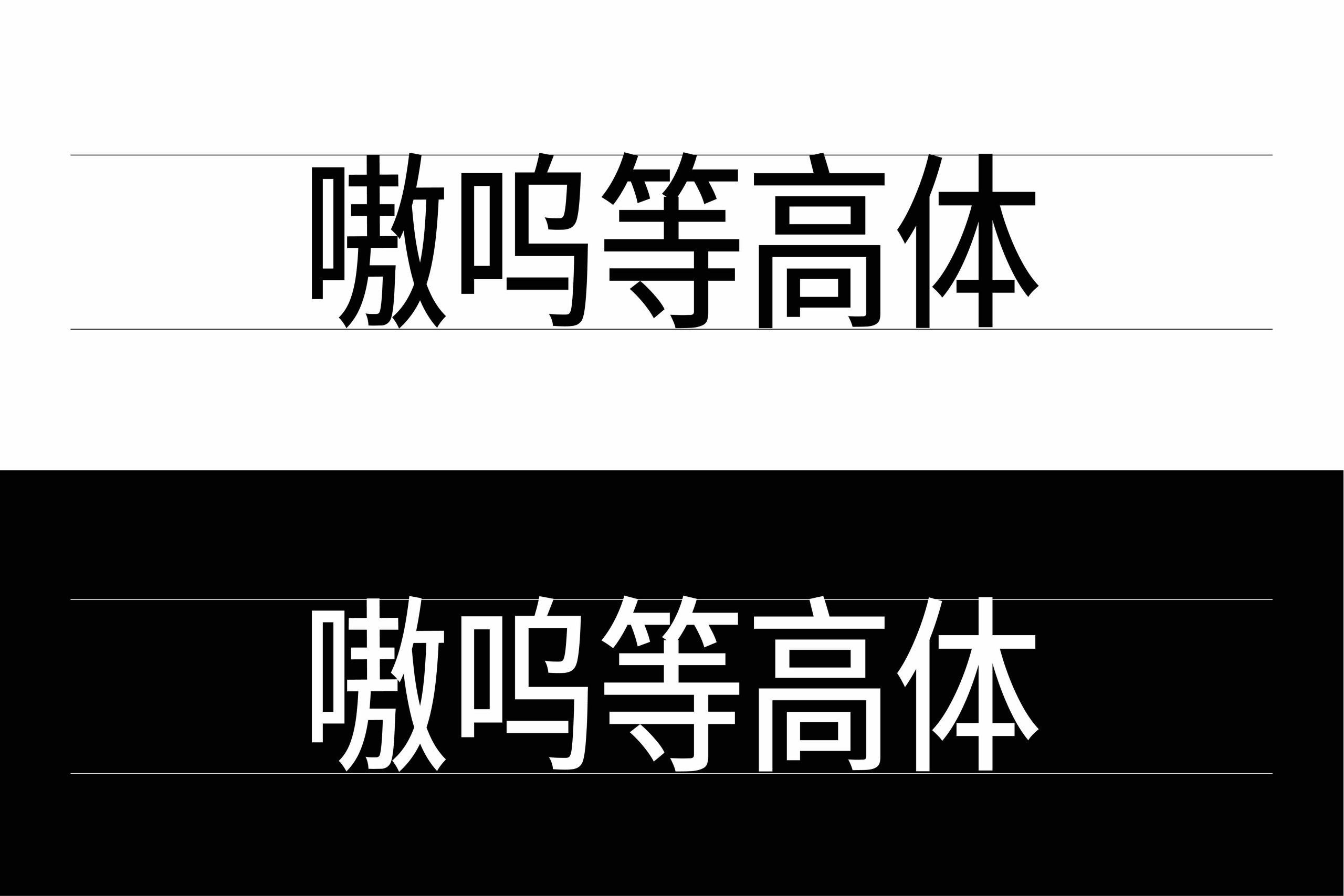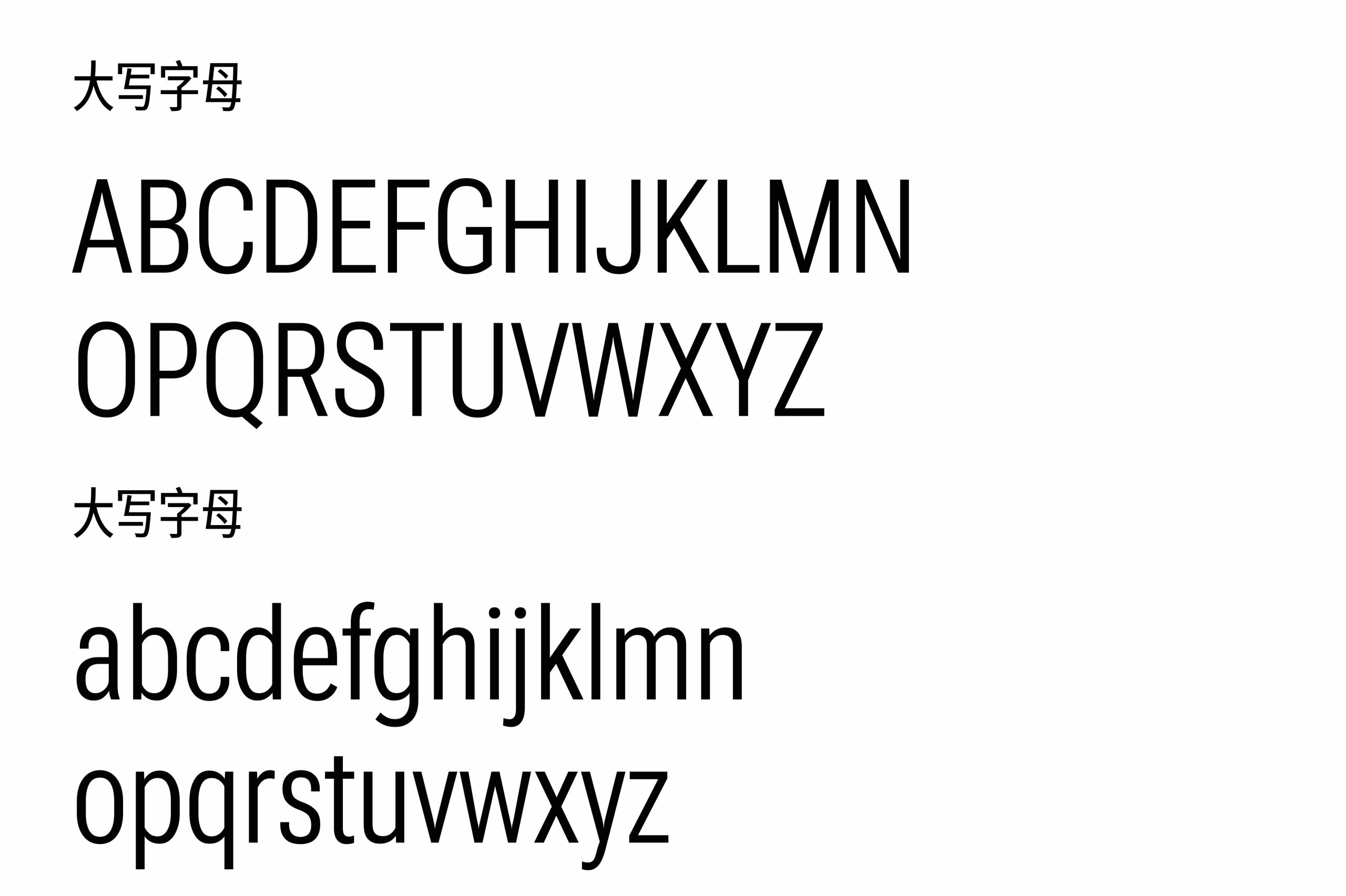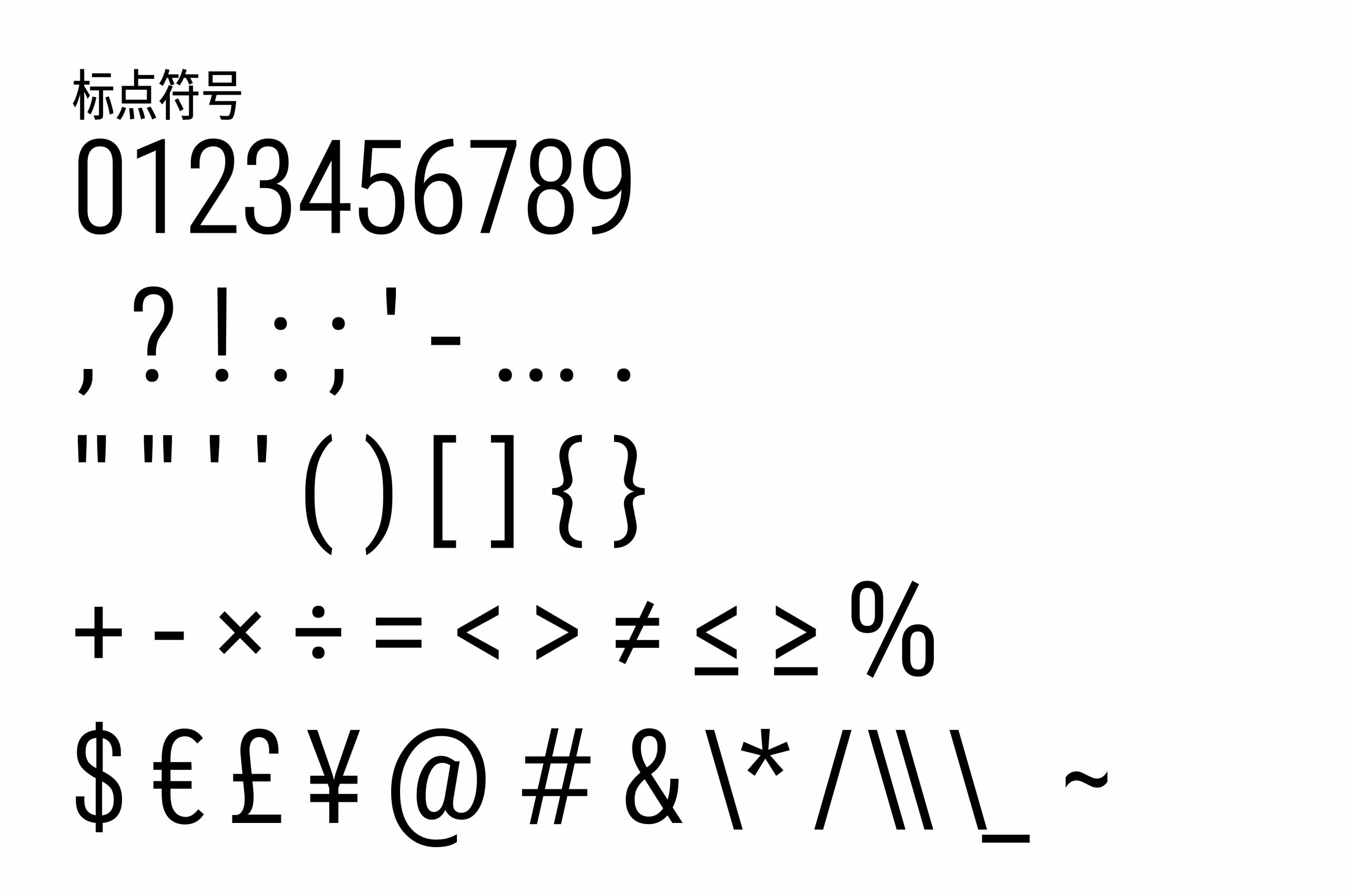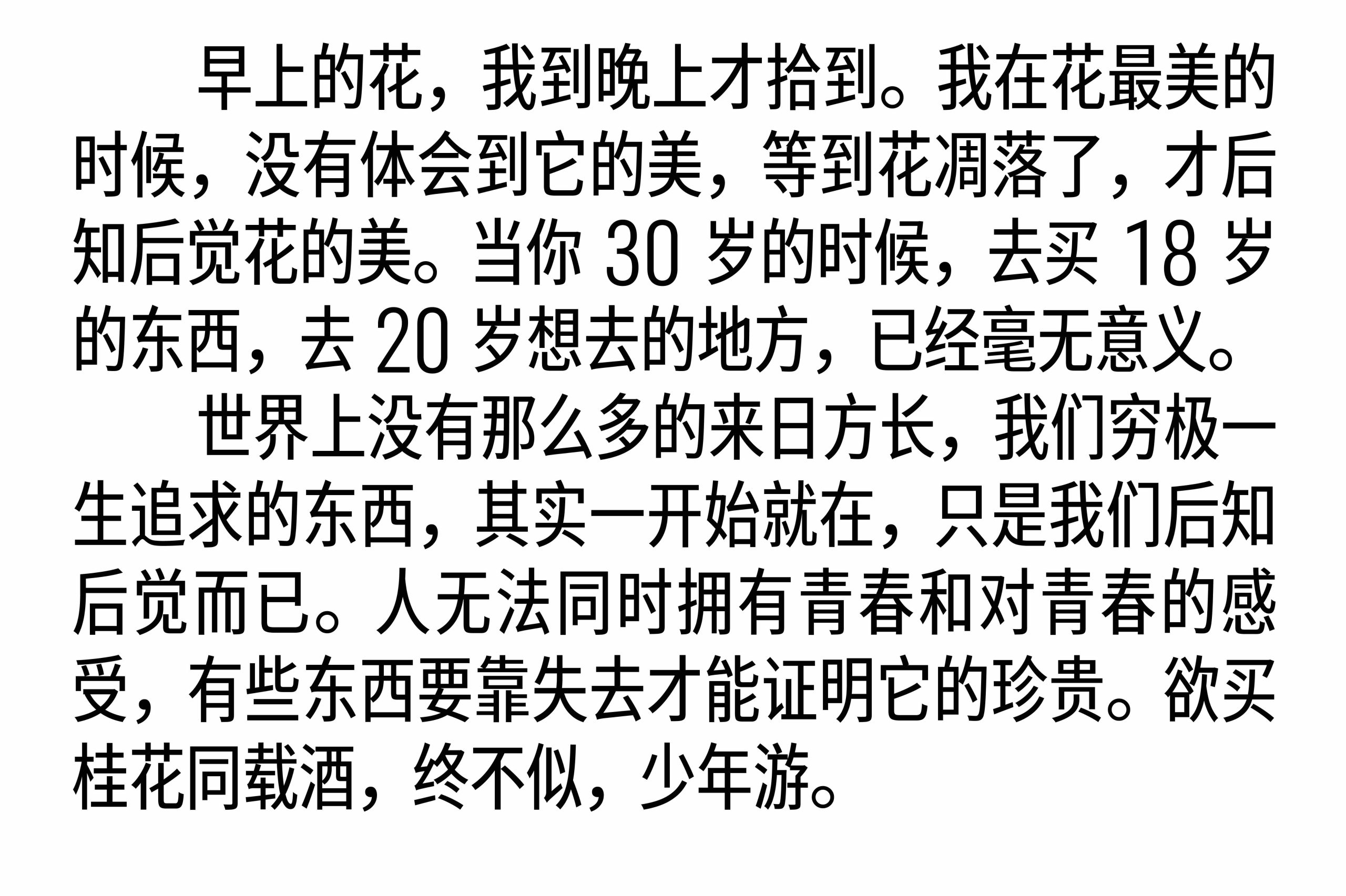
嗷呜等高体
字体介绍
在中文与西文混合排版中,汉字与英文、数字由于字面高度和字体结构存在差异,即使设置相同的字号,也很容易出现视觉高度不统一的问题。对于普通文本排版而言,这种差异并不一定明显,但在商品标签、包装设计、品牌视觉以及信息展示等需要强调文字整齐度的场景中,却往往需要设计师反复调整字号、位置和间距。嗷呜等高体正是针对这一实际排版需求制作的一款中文字体,通过对汉字与西文字符比例关系进行调整,使两者在排版时能够保持更加统一的视觉高度,为中西文混排提供更高效的字体解决方案。
嗷呜等高体:汉字西文等高的可变字体
从字体整体风格来看,嗷呜等高体采用简洁现代的无衬线设计,汉字结构规整,笔画简洁利落,英文与数字则保持较为修长的字形比例。与传统中文字体直接搭配西文字体相比,嗷呜等高体更加注重不同字符之间的高度关系,因此在中英文、中文与数字混排时能够形成更加整齐的版面效果。尤其是在需要连续排列商品名称、规格、型号以及参数信息的设计中,字体本身的等高特性能够减少后期对单个字符进行缩放和位置调整的工作。
嗷呜等高体:汉字西文等高的可变字体
嗷呜等高体的设计基础来自开源字体项目,其中西文部分基于 Roboto Flex,中文部分基于文渊黑体进行修改与优化。在保留原有字体简洁、现代的视觉特征基础上,项目进一步针对中文与西文混排时存在的高度差异进行调整,使汉字、大写英文字母以及数字能够在同一排版环境中获得更加接近的视觉高度。这种设计思路并非单纯改变字体外观,而是从实际使用场景出发,对字体的字面比例和排版关系进行优化,因此具有较强的实用属性。
嗷呜等高体:汉字西文等高的可变字体
除了汉字与西文等高这一核心特点之外,嗷呜等高体还支持字重与字宽双轴可变。可变字体的加入让字体不再局限于固定的几个字重和字宽,而是能够根据具体的版面需求进行更加细致的调整。在设计空间较为充裕时,可以选择相对舒展的字宽;当标签或者包装上的文字内容较多时,则可以适当收窄字宽,以获得更好的信息密度。同时,字重轴也可以根据标题、正文以及不同视觉层级进行调整,使同一套字体能够适应更多不同的设计需求。
嗷呜等高体:汉字西文等高的可变字体
对于商品包装和标签设计而言,这种可变特性尤其具有实际价值。商品信息通常同时包含中文、英文和数字,例如产品名称、规格、容量、型号等内容,如果分别使用不同字体进行组合,设计师往往需要额外处理字符高度、字号和基线之间的关系。而使用嗷呜等高体后,可以在统一字体体系下完成这些内容的排版,并通过字重和字宽变化适应不同尺寸的设计区域,从而减少人工调整所需要的时间,也能够让最终版面更加统一。
在实际应用方面,嗷呜等高体适合用于商品标签、产品包装、品牌视觉、海报标题、展览信息、产品参数以及中西文混排设计等场景。尤其是对于需要大量使用数字和英文字母的商品标签、包装信息来说,等高设计能够让不同字符之间的排列更加规整。对于强调简洁、现代视觉风格的品牌设计,也可以利用其较为修长的西文和数字造型构建更加清晰的视觉层级。
从字体展示效果来看,嗷呜等高体还提供了较为完整的西文大写、小写字母、数字以及常用标点和特殊符号。大写字母具有明显的现代无衬线特征,小写字母则保持简洁清晰的字形结构,数字和符号同样采用统一的视觉语言。这使得字体不仅能够承担中文标题和正文,也可以用于英文短句、数字信息以及各种符号组合,在需要中文、西文和数字共同出现的版式中具有较好的完整性。
总体而言,嗷呜等高体并不是一款单纯追求视觉风格的中文字体,而是一款围绕实际排版问题进行针对性优化的字体。它将汉字与西文等高作为核心设计特点,同时加入字重和字宽双轴可变功能,在保持现代无衬线风格的基础上进一步提升了字体的排版灵活性。对于经常处理商品标签、包装设计以及中文与英文混合排版的设计师来说,嗷呜等高体能够减少不同字体之间反复调整的工作,让文字在版面中更加统一、整洁,也为中文字体在实际商业设计中的应用提供了一种更加实用的选择。